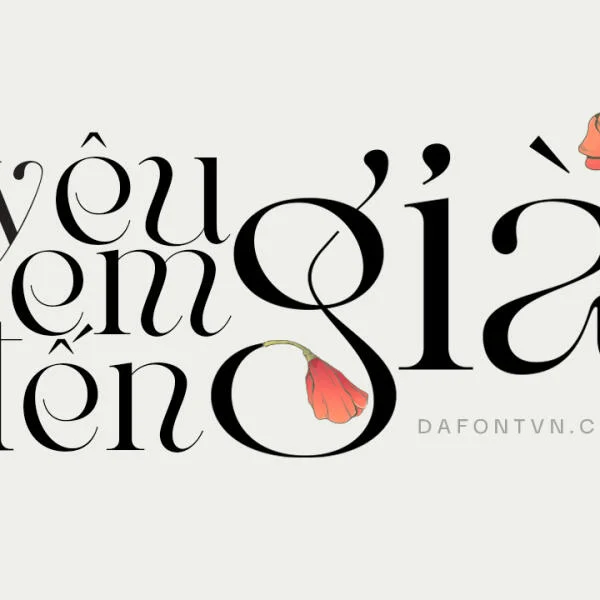
Tải Font Abygaer Việt hóa - 1 kiểu font có chân tuyệt đẹp
Tổng quan về Font Abygaer
Abygaer việt hóa một font chữ hiện đại với OpenType khá đầy đủ cùng nhiều phong cách khác nhau với các kiểu chữ uốn lượn hài hòa nhằm tạo nên nhiều kiểu chữ sang trọng và độc đáo hơn. Abygaer là font chữ vintage được lấy cảm hứng từ các biển hiệu thời xưa cũ và được việt hóa font cùng các dấu theo phong cách xưa cũ. Có thể nói đây là font chữ có nét chữ cứng cáp nhưng nó lại mang đến một vẻ đẹp quyến rũ riêng.
Một số lượng lớn các chữ ghép OpenType đan xen và xen kẽ, có nghĩa là bạn có nhiều lựa chọn và sự đa dạng trong việc thiết kế của mình. Phông chữ phù hợp cho nhiều thiết kế khác nhau như tiêu đề, bìa sách, tạp chí, xây dựng thương hiệu, thiết kế typography...
Chi tiết ký tự Font Abygaer